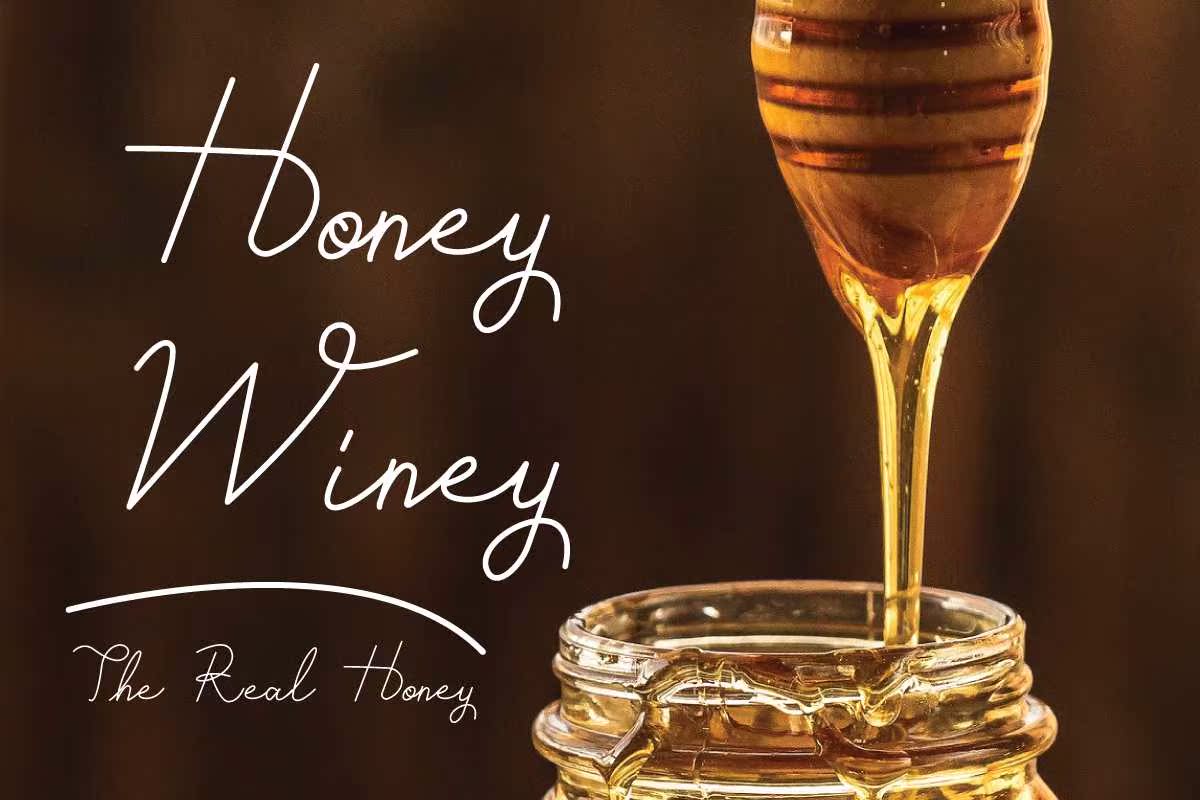
它可能是一种简洁、优雅、流畅的书写字体。它具有美丽、平衡的特点,因此,它与广泛的设计资源相匹配。除了你最具创造性的想法之外,它还可以让你注意到它是如何让你的生活充满活力的!Asta可能是一款用LegantTouch描述的字体,非常适合您喜爱的项目。爱上它令人难以置信的独特和永恒的样式,并使用它来创建壮观的设计!它可能是一种简洁、优雅、流畅的书写字体。它具有美丽、平衡的特点,因此,它与广泛的设计资源相匹配。除了你最具创造性的想法之外,它还可以让你注意到它是如何让你的生活充满活力的!Asta可能是一款用LegantTouch描述的字体,非常适合您喜爱的项目。爱上它令人难以置信的独特和永恒的样式,并使用它来创建壮观的设计!